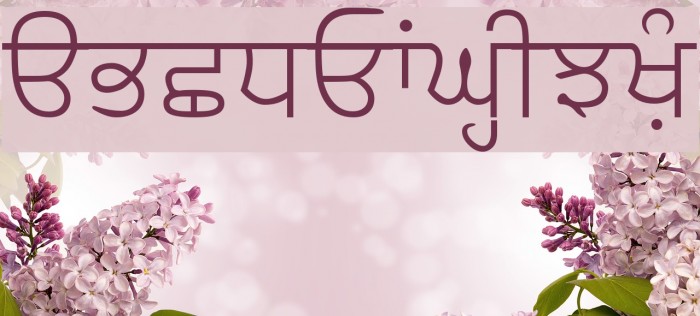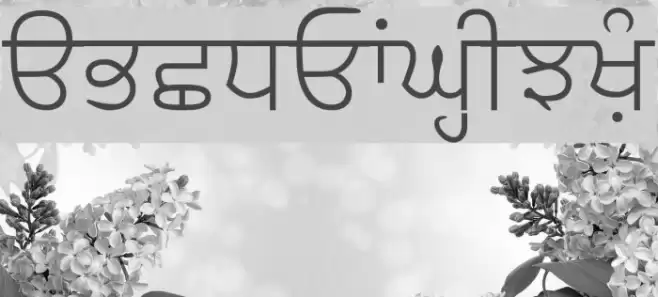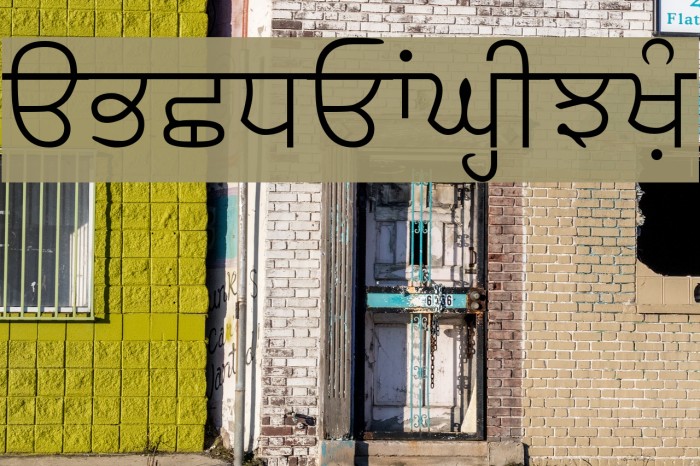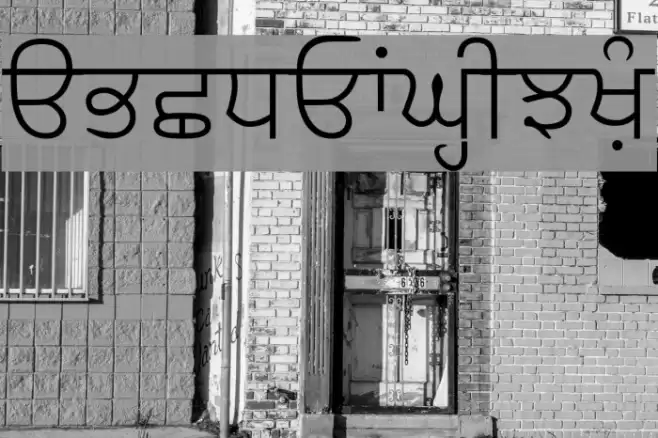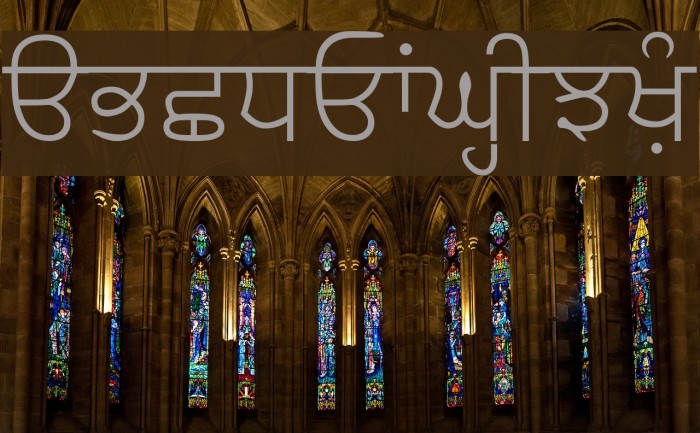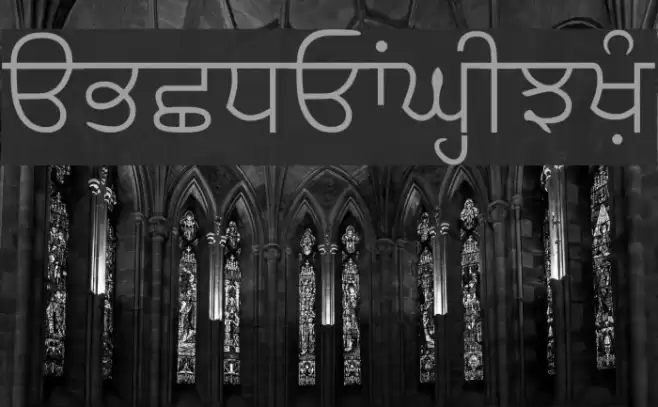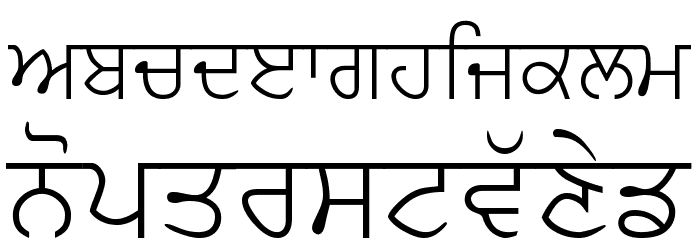
SamtolLight Font
| Proiecte propuse | This font is perfect for branding projects, editorial design, web design, and advertising materials where a modern and professional look is desired. |